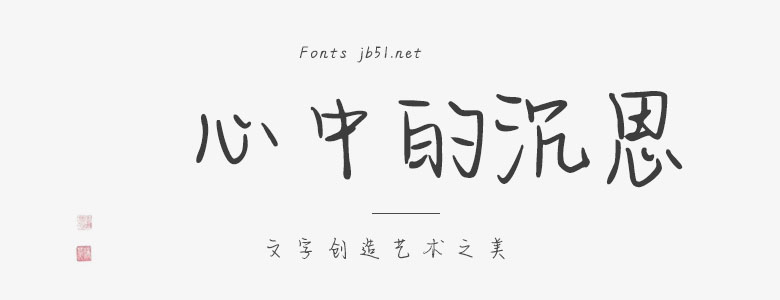
海浪拍打沙灘,涌動的潮音引發(fā)心中的沉思。該字體是在國家標準簡體字庫GB2312所包含6763漢字的基礎(chǔ)上,又增加了近200常用字,已經(jīng)覆蓋了大陸99.75%的漢字使用頻率,足以滿足日常需求,適合于文化類的宣傳設(shè)計、商業(yè)類品牌的廣告和產(chǎn)品包裝設(shè)計以及個性化文字排版等較多場景.